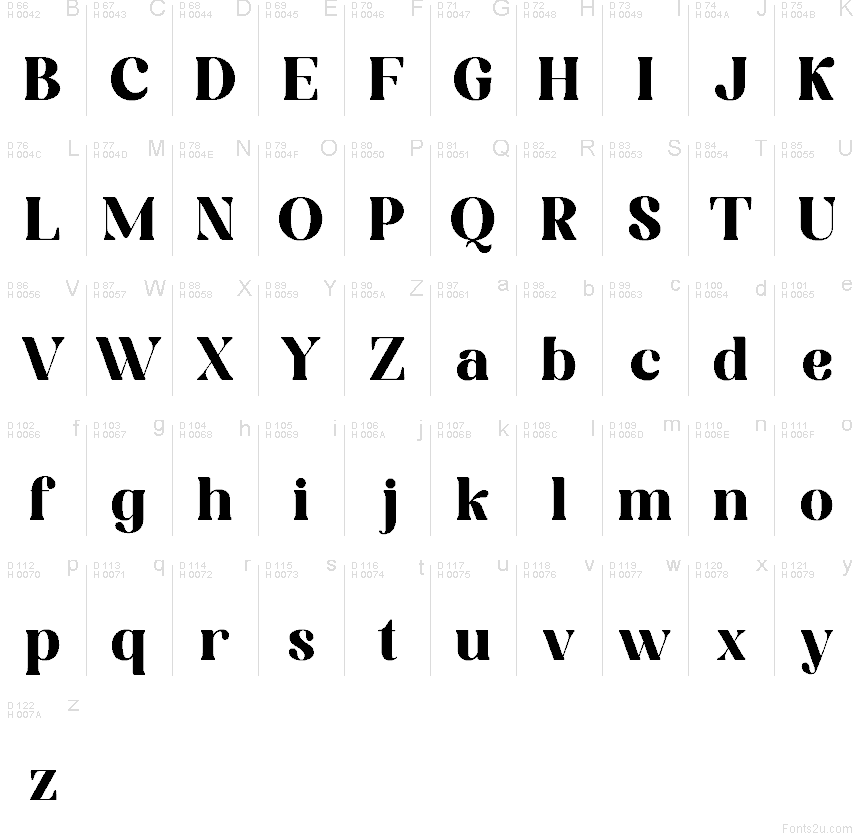
Sodabery od Taboja Studio to darmowy, wysokokontrastowy krój szeryfowy o modowym, redakcyjnym charakterze, łączący szerokie, zaokrąglone formy z precyzyjnie wyciętymi krawędziami. Zamaszyste krzywizny i dramatyczne przejścia między grubymi a cienkimi liniami nadają literom pewny, niemal teatralny rytm.
Jako darmowy font, Sodabery Regular doskonale sprawdzi się w winietach redakcyjnych, na opakowaniach perfum, w identyfikacjach butikowych, na okładkach albumów oraz eleganckich planszach tytułowych. Świetnie odnajduje się także w krótkich nagłówkach i napisach okładkowych, gdzie hojne krzywizny i wyraźny kontrast mają przestrzeń, by w pełni zaprezentować swój urok.